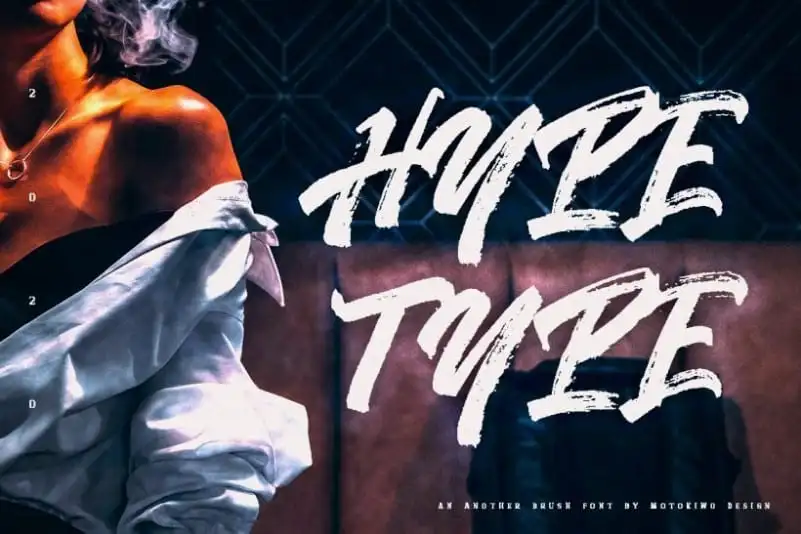
A Hypetype Brush Font é uma coleção meticulosamente selecionada de fuentes escritas a mão recentemente criadas, projetadas para complementar-se perfeitamente entre si. Ela faz parte de um pacote essencial para qualquer iniciante no design gráfico, pois todas as fontes são de alta qualidade e estão disponíveis para qualquer projeto. Feita pelo designer Motokiwo, esta é uma fonte com textura natural e estilo paint-brush ativo. Suas características tornam o texto único em qualquer arte ou projeto. A Hypetype Brush Font é ideal para aplicações que incluem outdoors, headlines ou qualquer outro tipo de design gráfico. Com todas as letras maiúsculas, números e pontuações inclusas, a fórmula de Motokiwo proporciona algo novo e interessante em cada projeto. Esta fonte de escrita a mão permite um toque autêntico ao seu design, tornando-a uma opção perfeita para quem busca uma personalização única.